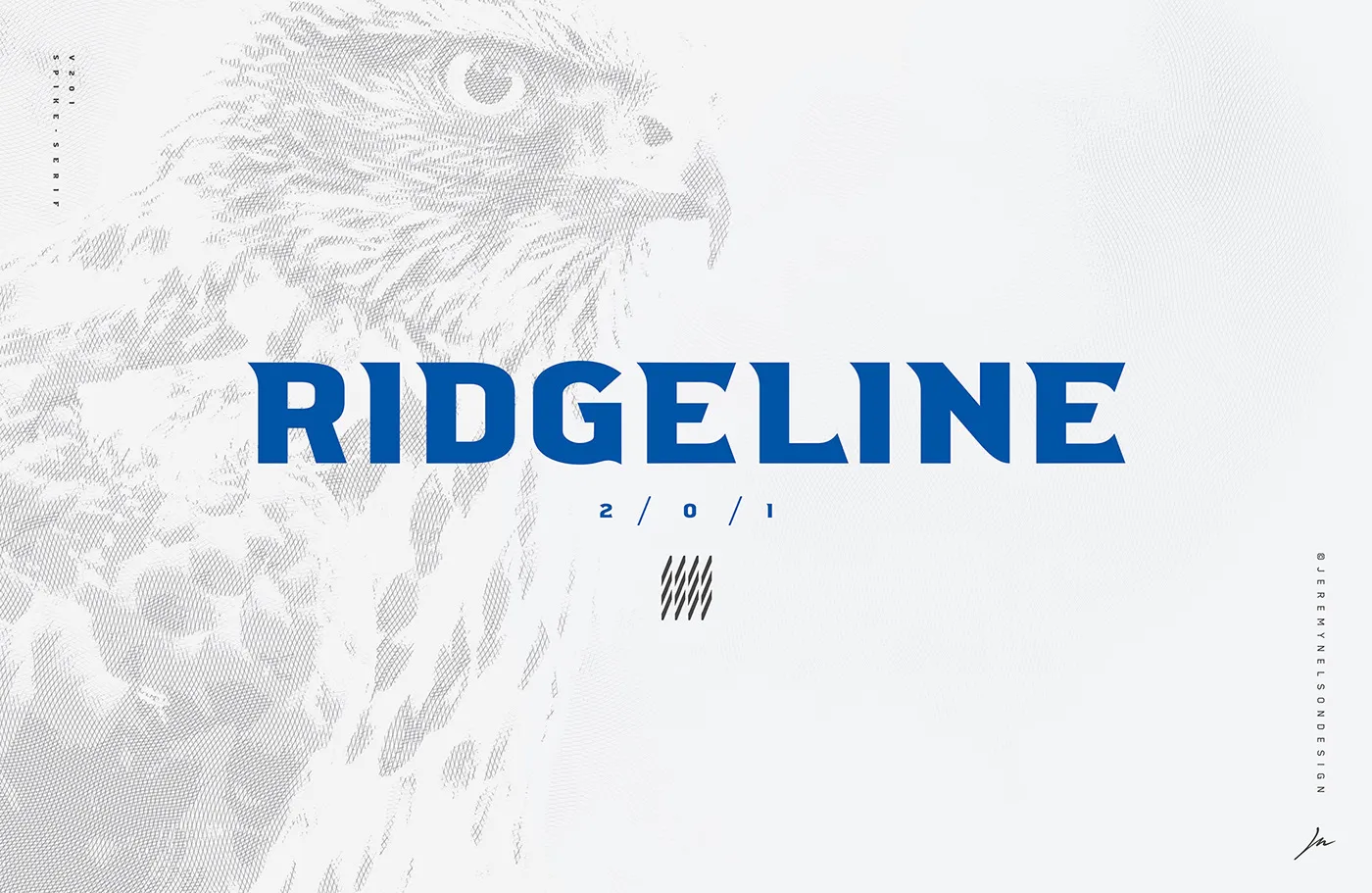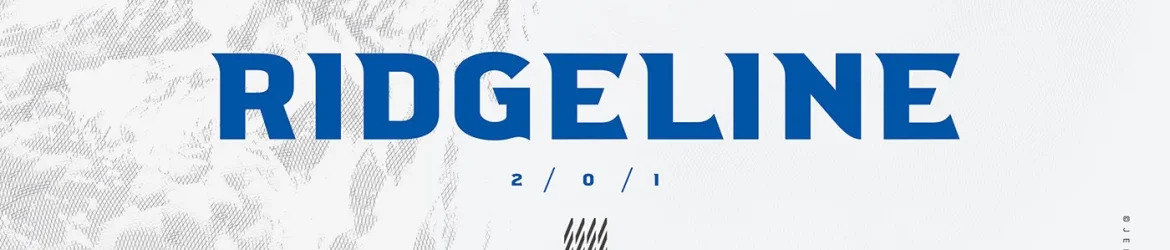
Ridgeline 201 Typeface – Download Grátis
Introduzimos a nossa primeira tipografia geométrica neste lançamento emocionante, introduzindo Ridgeline 201. Desenhada por Jeremy Nelson, esta tipografia serif apresenta uma inspiração ativa e vanguardista. Com suas linhas retas e robustas, Ridgeline 201 transmite velocidade, agilidade e poder de forma elegante e eficaz. Perfeita para uso em cartões de visita, materiais de marca, postais, editoriais, slogans e até mesmo na design de roupas, Ridgeline 201 é um verdadeiro atalho para a expressão visual em uma ampla gama de ambientes. Seu estilo arquitetônico e forte faz dele um aliado ideal para designers que procuram manter sua identidade visível e imprimível na era digital atual.